最佳網站字體以及如何選擇正確的字體
已發表: 2022-02-11從配色方案到字體和標題設計,如果我們談論的是像您的網站這樣的大型數字項目,每一個小細節都很重要。 使用不同的字體和字體效果可以給您的用戶帶來負面和正面的影響,正面還是負面完全取決於您。 平衡是一種將所有這些細節連接到一個組織良好的創作中的和諧方式,對於每個數字設計師來說都是至關重要的。
字體和字體效果是實現這種平衡的最佳方式,因為對於大多數網頁而言,最重要的視覺數據量被正文、標題和標題佔據。 因此,您可以調整簡單和復雜細節的數量,以獲得完美的結果。
打開 Sans
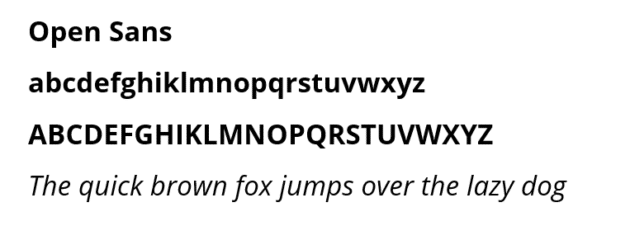
Open Sans 是無襯線字體的一部分,旨在提供最高的可讀性和用戶體驗。 這種網絡字體是具有大量信息(博客、信息文章等)的簡約網站的最佳選擇。 這種字體的另一個好處是它與許多不同的風格兼容。
拉托
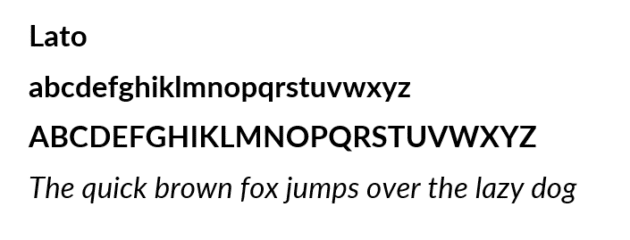
如果您的網站在金融、法律甚至會計等嚴格領域中激活,Lato 是最好使用的字體之一。 該網站字體易於使用,更多地被認為是一種體現高度專業性的公司字體。 對於那些想要以現代方式豐富網站設計的人來說,Lato 是最好的字體。
黑爾維提卡
作為全球最常用的網站字體之一,瑞士設計師 Max Miedinger 發現了 Helvetica。 Helvetica 因其令人難以置信的款式和尺寸而廣受歡迎,這有助於設計師為他們的特定創作選擇最佳版本。
梅里韋瑟
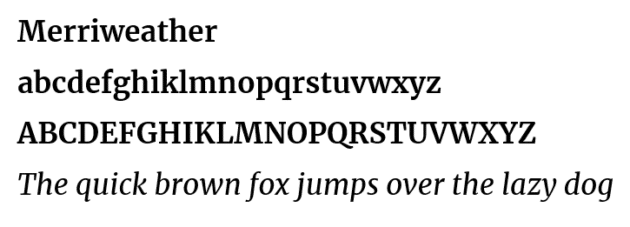
如果您有不同的受眾在大屏幕和小屏幕上閱讀您的內容,那麼 Merriweather 網站字體是您必須選擇的字體。 這種成比例的字體結合了時尚的外觀和簡約的風格,這是一種驚人的合併,在各個領域的網站上都有很大的潛力。 Merriweather 非常適合正式和非正式風格。
遊樂場展示
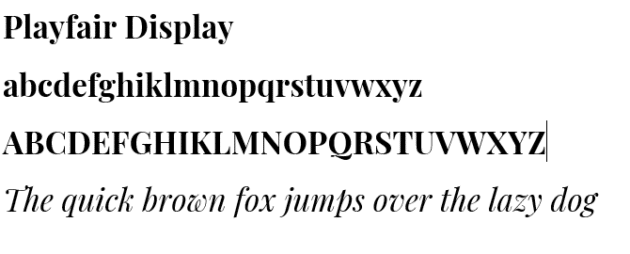
Playfair Display 是一種帶有一點經典特徵的時尚字體。 如果您為複雜的網站選擇字體,Playfair Display 絕對是您的選擇。 它非常適合內容簡單、美觀且內容易於理解的網站。 事實上,Playfair Display 的可讀性不如其他字體; 它的主要優點是類。
蒙特塞拉特
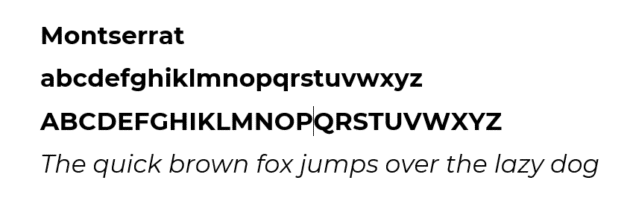
這種無襯線字體幾乎是您可以選擇的最佳網站字體。 它的幾何風格通常允許您找到一種在您的網站上實現它的方法。 儘管蒙特塞拉特非常時尚,但很多人發現它在小屏幕和大屏幕上都可以閱讀。
自由巴斯克維爾
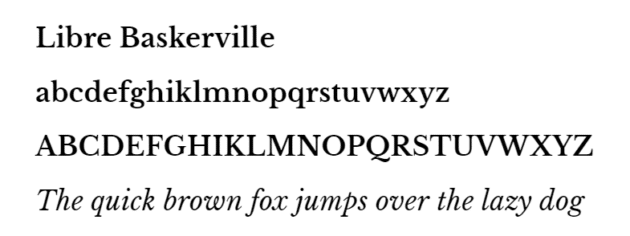
Libre Baskerville 是一種襯線字體,其靈感來自其 18 世紀的前身。 其經典風格非常適合用於經濟、體育和美容等廣泛領域。 儘管 Libre Baskerville 非常受歡迎,但如果您的受眾使用大屏幕訪問您的網站,這不是最佳選擇,因為當字體太大時字體看起來不太好。
考德斯
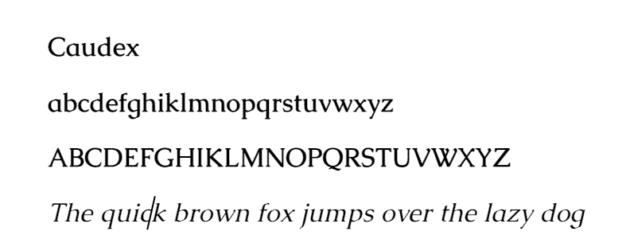
最初用於中世紀手稿,Caudex 在 90 年代後期進行了改革並適應了我們的現實,此後一直沒有停止發展。 Caudex 可用於段落和標題,毫無疑問,它是可用樣式種類最多的字體。 它適用於大屏幕和小屏幕。
巴洛
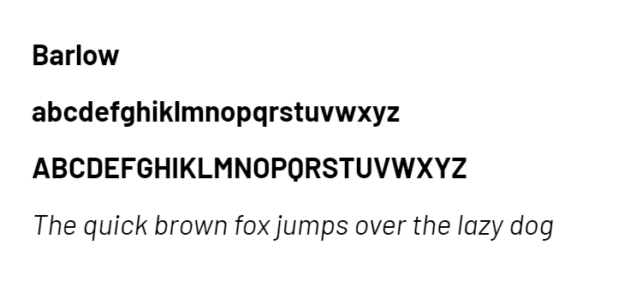
這種無襯線字體 Barlow 似乎受到了加州車牌和高速公路標誌的啟發。 其簡潔的設計可以為您的網站帶來一些流暢性,使其更加舒適和易於閱讀。 這種字體的另一個好處是與您網站上的許多其他字體的兼容性。
機器人
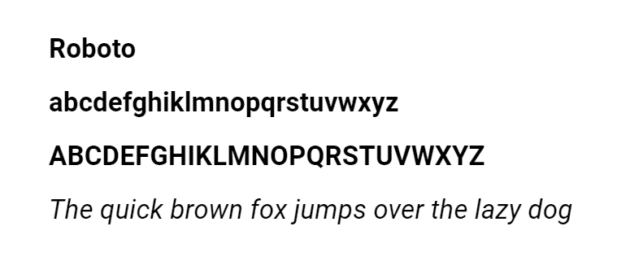
簡單明了是完美描述Roboto字體的形容詞。 其主要目的是將信息傳遞給您的客戶,而不會有任何復雜的風格。 它被認為是一種專業字體,但在某些情況下,設計師將這種字體用於友好的內容。
如何選擇合適的字體?
正確的字體通常是吸引更多網站用戶的關鍵。 因此,設計師正確選擇它的能力會對用戶體驗和他們的評論產生積極影響。
根據網站內容選擇字體
在大多數情況下,您網站的最大部分將包含不同類型的文本,這已經不是什麼秘密了。 因此,如果您想要一個時尚、佈局合理的網站,那麼實現這一目標的第一步就是為該文本選擇正確的字體。 最大的提示是不要在一頁上使用超過 3-4 種字體; 它看起來很糟糕而且很亂。 這就是為什麼,鑑於存在許多不同的字體,您應該特別選擇最適合您的字體,不要推得太遠。
人們最困惑的是結合字體和網站的設計來獲得一個偉大而時尚的合併。 事實上,它比你想像的要簡單得多。 有些字體最適合包含大量嚴肅和信息豐富的內容的網站,而有些字體則適用於有趣和膚淺的內容。 您需要了解您將要編寫的內容類型。 通常,Times New Roman 和 Robotica 等字體因其嚴謹和簡約的風格而用於信息內容,而 Playfair Display 等字體則非常適合休閒內容。
三種字體
就像我在上一段中所說的那樣,您的網站不應包含超過三種字體。 但是這三個是什麼,你如何選擇它們? 你會馬上知道的。
- 您將在標題、副標題和標題中使用的第一種字體至關重要。 這種主要字體應該與您的品牌直接相關並反映其理念。 如果您有一個極簡品牌,則主要字體應盡可能簡約,以反映其理念。 如果可能,您應該選擇與徽標中使用的字體相同的字體(如果有的話)。
- 輔助字體將用於編寫內容的最大部分。 即使您對網站的其餘部分進行了更複雜的設計,它也應該簡單易懂,因為這部分文本應該對您的大多數用戶盡可能可讀。 您不能選擇難以理解的時尚字體。 對於您網站的這一部分,它實際上是不可接受的。
- 第三種字體是可選的,用於突出文本的某些部分並更快地吸引讀者的注意力。 在這裡你可以使用一些更複雜的字體,但不要比你的次要字體推得更遠; 它們應該有一些相似之處才能完美結合。
請記住,您為網站選擇的字體和字體越多,就越難組合和協調它們。 一般來說,更多的字體意味著你的網站設計更混亂。 就這麼簡單。
了解基本情況
排版是一門藝術,就像每一種藝術一樣,很難在心跳中學習和理解其存在的方方面面。 但是,一些基礎知識可以幫助您為您的網站選擇正確的字體。 字體的分類對於每個必須為其網站選擇字體的設計師來說都是至關重要的。 在這裡,您將找到一個快速但內容豐富的摘要,這將幫助您了解它們之間的區別。
襯線字體:
當您輸入的信息最終將被打印時,通常會使用它。 經典而時尚的襯線字體因其優雅而不常用作網絡字體。 但是,如果您選擇撰寫有關金融、法律或時尚的文章,這是您的選擇。 Times New Roman、Georgia 和 Bodoni 是襯線字體。
無襯線字體:
這些字體不像襯線字體那樣在字母末尾有襯線。 現代而直接的網頁設計師通常使用這些字體,因為它們具有中性的外觀。 無論您寫什麼主題,都可以使用這些字體。 它們通常非常適合解決大量問題。 Helvetica、Robotica 和 Open Sans 是一些著名的無襯線字體示例。
腳本字體:
這些字體是根據手寫樣式建模的。 它們通常用於標題、副標題和突出顯示文本的一些重要部分。 您不能使用腳本字體來編寫正文,因為這對讀者理解和理解信息是一個挑戰。 Lobster 和 Lucida Handwriting 是腳本字體。
請記住,您為網站選擇的字體和字體越多,就越難組合和協調它們。 通常,更多的字體意味著您的網站設計更加混亂。 就這麼簡單。
另一個重要的基本知識是如何強調文本的不同部分。 通常,為了使某些細節從文本的其餘部分中脫穎而出,許多作者使用粗體或斜體。 這是一個不錯的選擇,但如果你想要原創,你可以使用我上面描述的不同類型的字體,第三種字體用來強調。
不要忘記加載時間
我們生活在一個人所能擁有的最寶貴的資源就是時間的時代。 因此,沒有人願意等待網站加載很長時間才能看到更複雜或更漂亮的字體。 通常,這個人會選擇另一個站點來更快地接收他需要的信息。 正確選擇字體可以顯著提高網站的速度。 怎麼做? 這裡有一些提示。
- 您已經知道為什麼單個網站上的大量字體是您能做的最糟糕的事情的許多原因。 這是堅持使用 2 或 3 個的另一個原因。 更多字體意味著必須處理的數據量更大,這需要時間。
- 不要用很多美麗但無用的東西使設計過於復雜,這只會使事情變得更糟。 例如,為標題和標題使用設計良好的字體是一件好事。 但是對於正文,選擇像 Robotica 或 Helvetica 這樣的基本字體更合理。